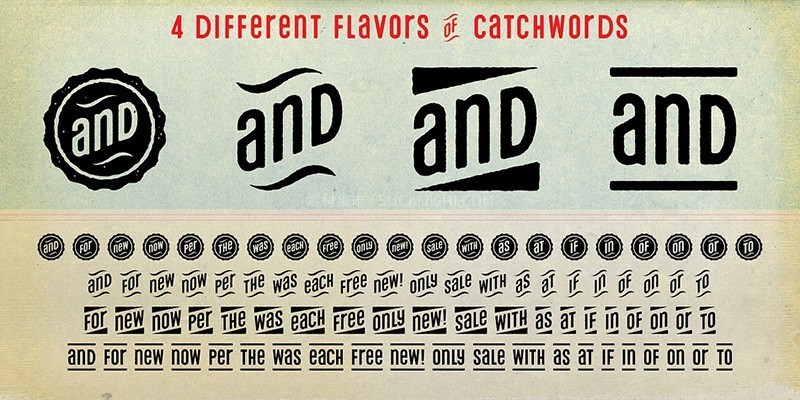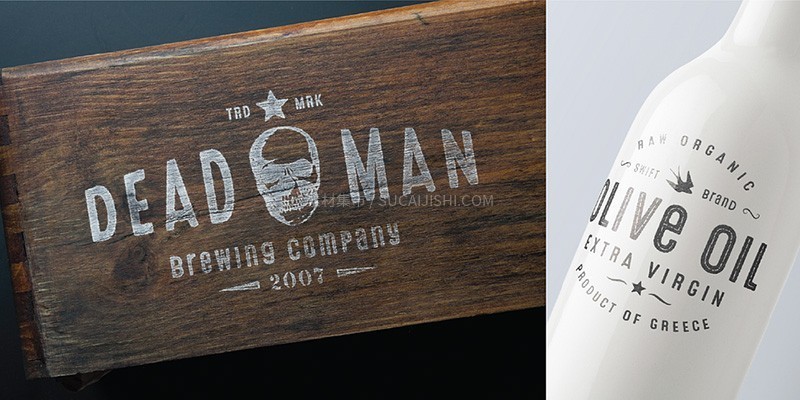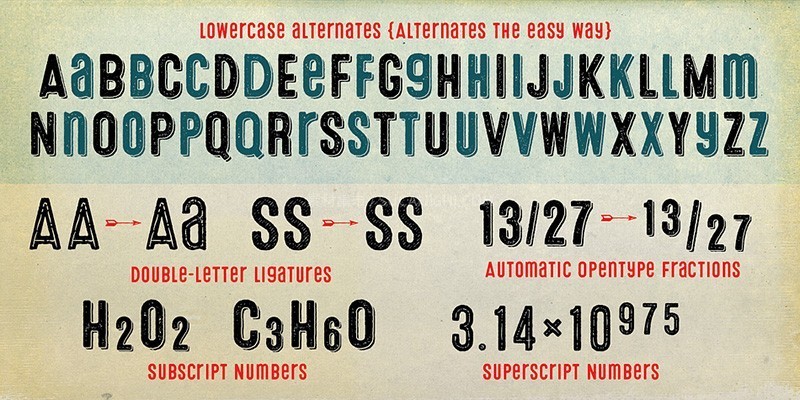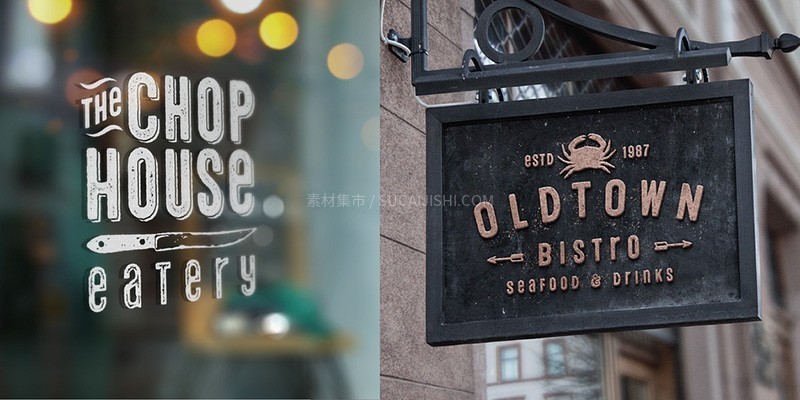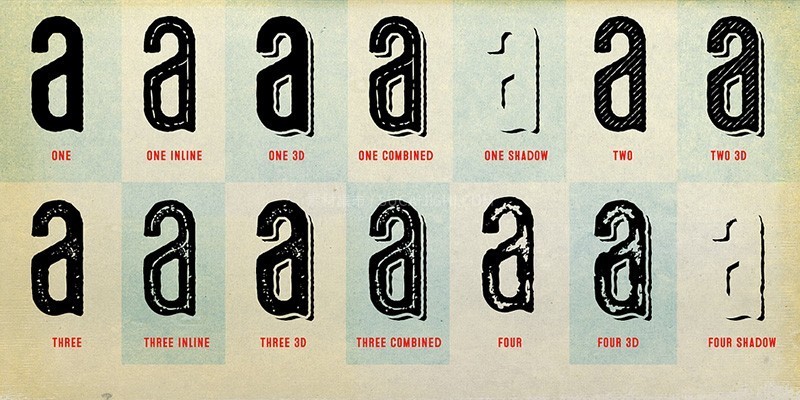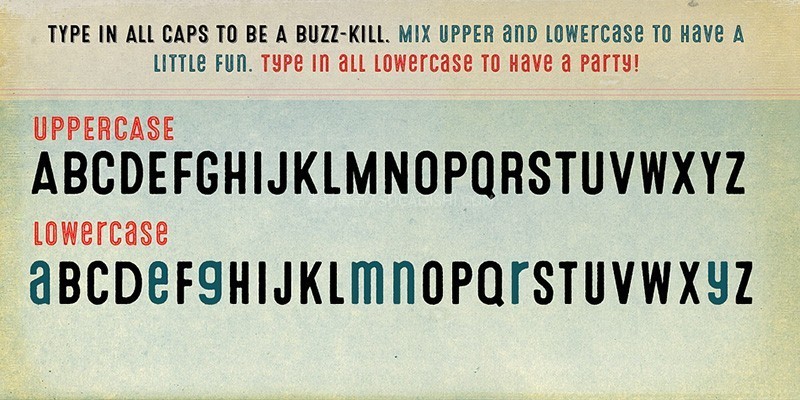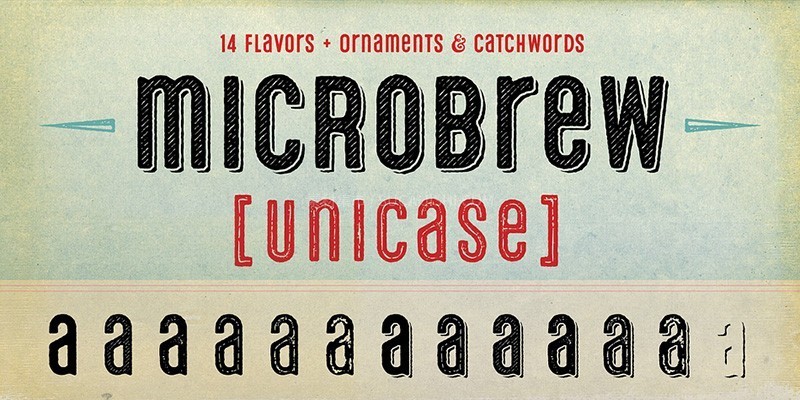
Microbrew Unicase 复古凸版印刷字体家族
Microbrew Unicase 是 Microbrew 系列的最新力作,融合了木质海报与复古凸版印刷风格。拥有 14 种独立风格和一套实用标语/装饰,细节丰富的风格适合大尺寸展示,简洁风格则在小尺寸下更易读。这款全大写字体,通过大小写混合输入即可实现有趣的字形替换和更真实的双字母连字,轻松营造复古质感。用途广泛,适用于从餐厅咖啡到婚礼音乐的各种主题设计。